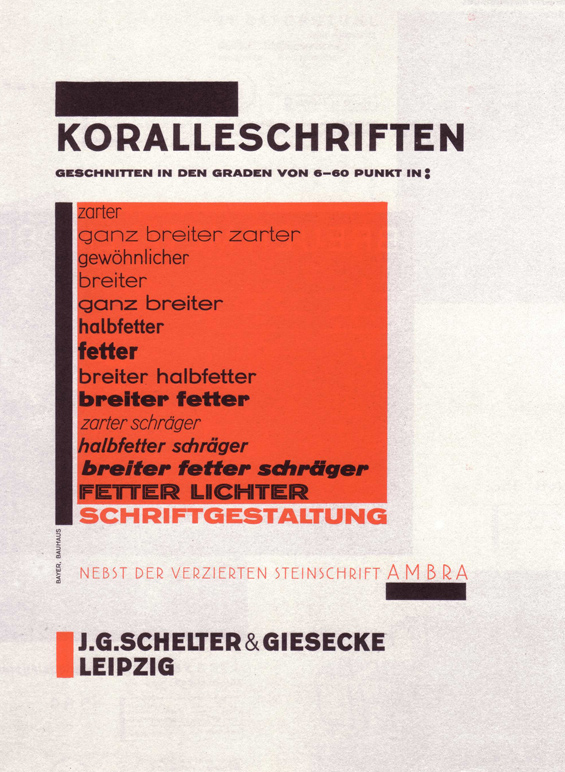
Herbert Bayers Universal-Plakat: die Ergänzungsschrift?
Ich suche verzweifelt die Ergänzungsschrift auf Herbert Bayers berühmten Universal-Blatt.
Also nicht die "sturm blond"-Typo, sondern "Beispiel eines Zeichens in größerem Maßstab ...".
Grund: Ich will das Blatt vektorisiert nachbauen, weil ich's in keinem Poster-Shop finden kann - und bin mit der Universal auch schon fertig. Fehlt nur noch die Komplementär-Typo, und da bin ich trotz hartnäckigen Forschens ratlos geblieben.
Markant sind vor allem das geschlossene "a", das gestutzte "g" und die breiten Anführungszeichen ...
die FF Bau/Scheltersche hatte ich auch schon im Blick. Aber bei der ist das "a" offen, und das "g" hat eine Schleife.
Vielleicht hatte Bayer eine Variante? Denn nah dran, da stimme ich dir zu, ist sie schon ...
Aber wo, zum Teufel, kriege ich die jetzt her? Gibt's die überhaupt digitalisiert?
Oder zumindest ein halbwegs gut aufgelöstes Muster mit ein paar Lettern mehr?
Hmmm, muss ich am Ende doch von Hand ran ...